1、汉标高清锐毛书法味道的纯手写字体,作者运用大号毛笔精心书写,楷书味道浓厚,由于字体较大,使得笔画清晰度较高,笔画中也减少了过多的处理和笔势,厚重、饱满。因为是纯手写的原因,它独特的气质更与其他字体不同,看似统一,其实各有各的味道,每个字都可以独具风情。
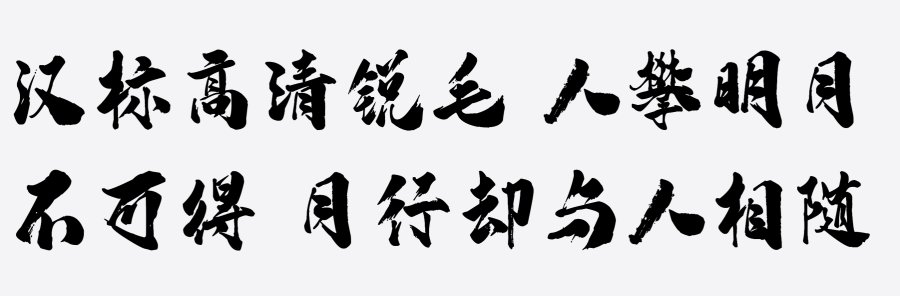
2、刀锋楷书字体是施申财字库推出的一款个性行楷字体,字体书写颇具个性,具有很好的视觉感,适合艺术设计、平面宣传设计、网页设计、书法字帖等领域。
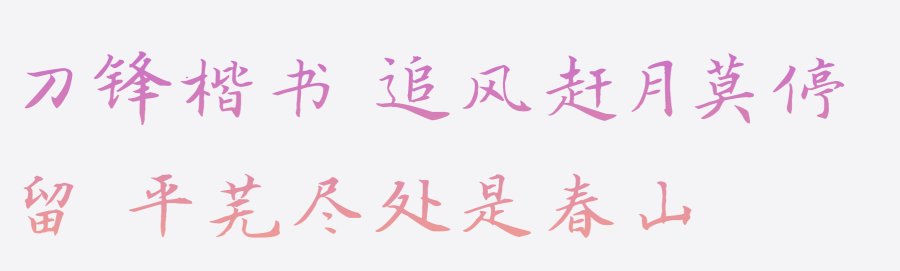
3、华光布小兜体是一款创意卡通字体。高光的点缀使整个字体饱满立体,笔画风格及其可爱,圆润中透着可爱,让人爱不释手。